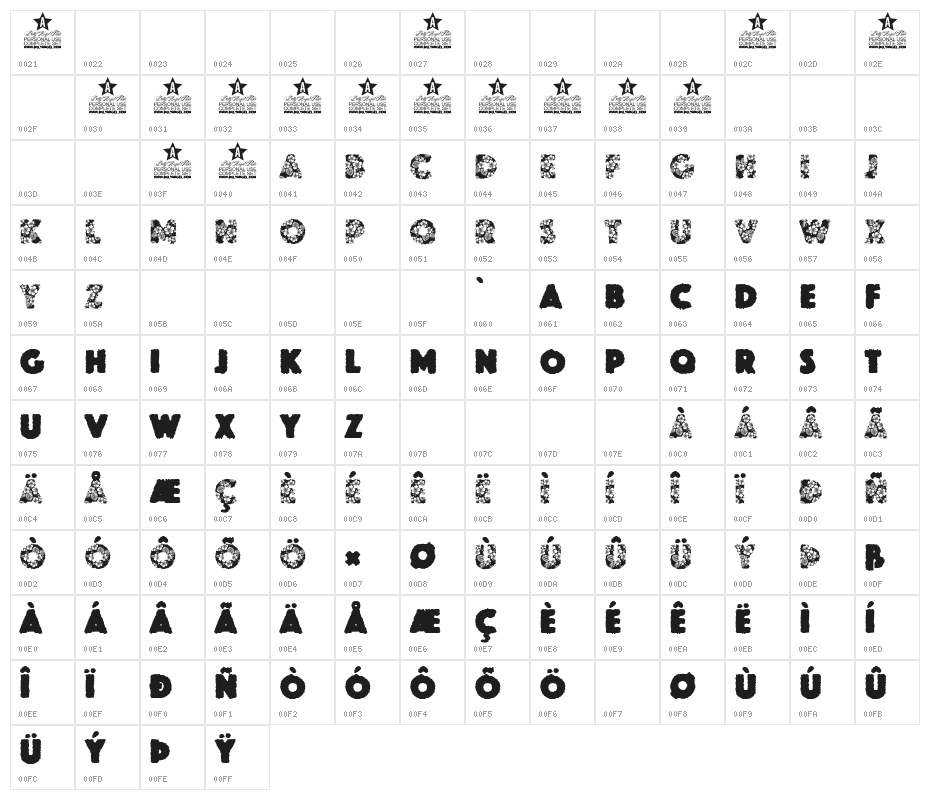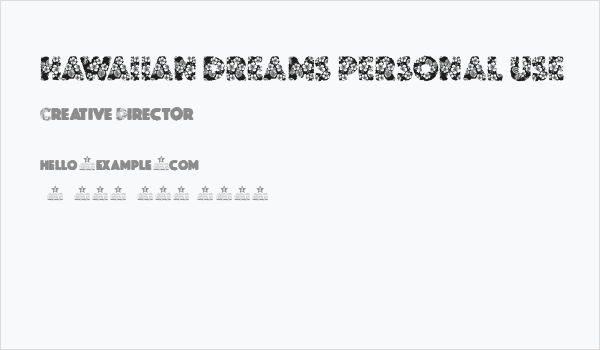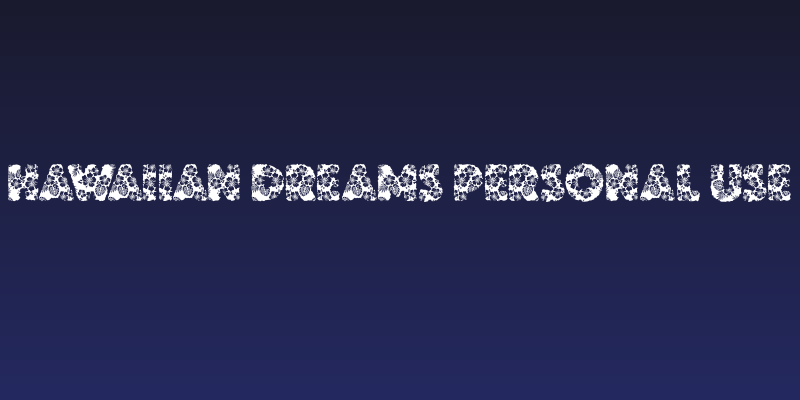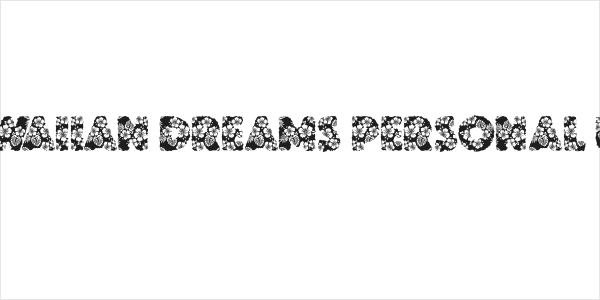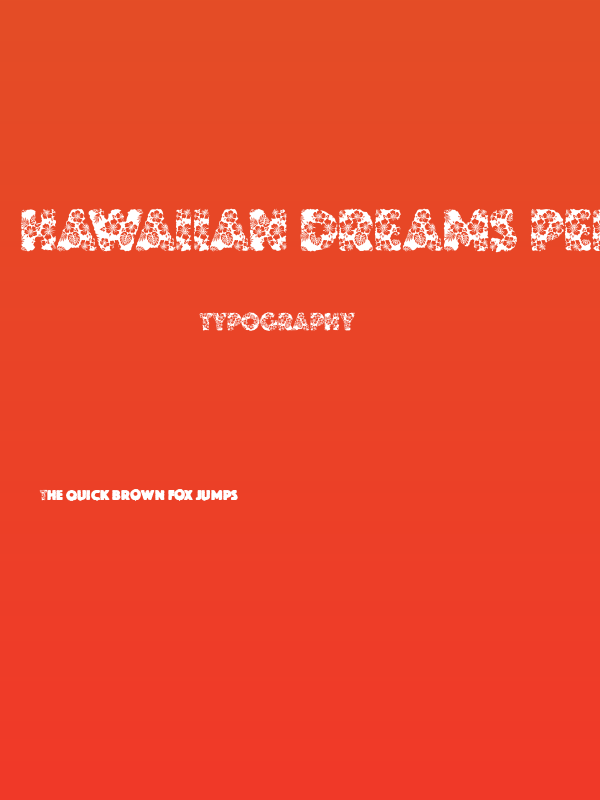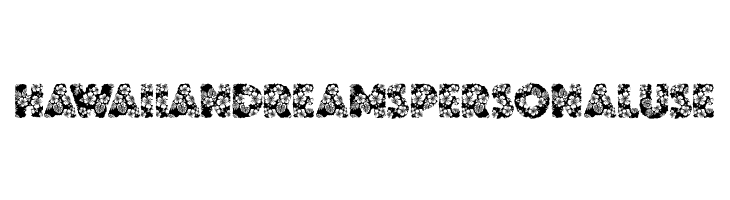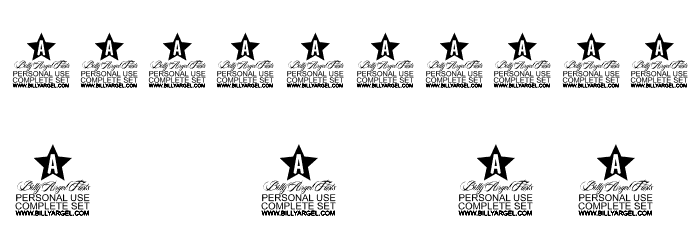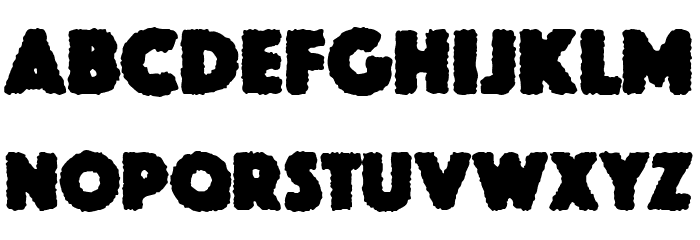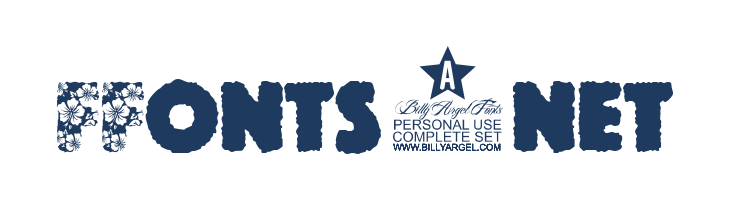
HAWAIIAN DREAMS PERSONAL USE Font
| おすすめプロジェクト | Ideal for beach-themed event posters, tropical party invitations, summer festival branding, and creative merchandise designs. |